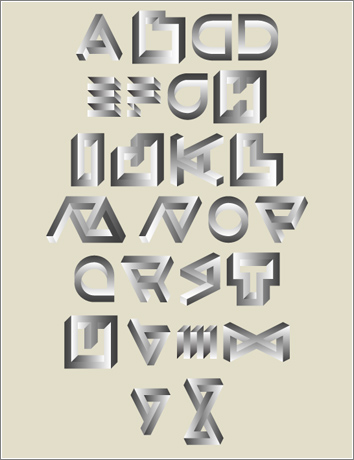
Typographisme Escher, una tipografía experimental, con reminiscencias Escherianas, basada en cierto modo en el efecto del triángulo de Penrose, donde cada letra tiene algún toque de «imposibilidad».